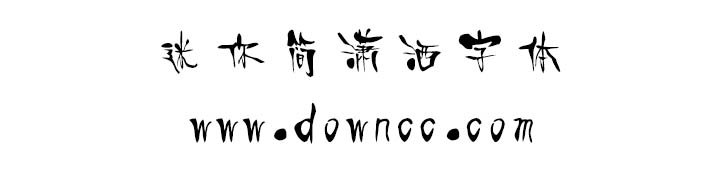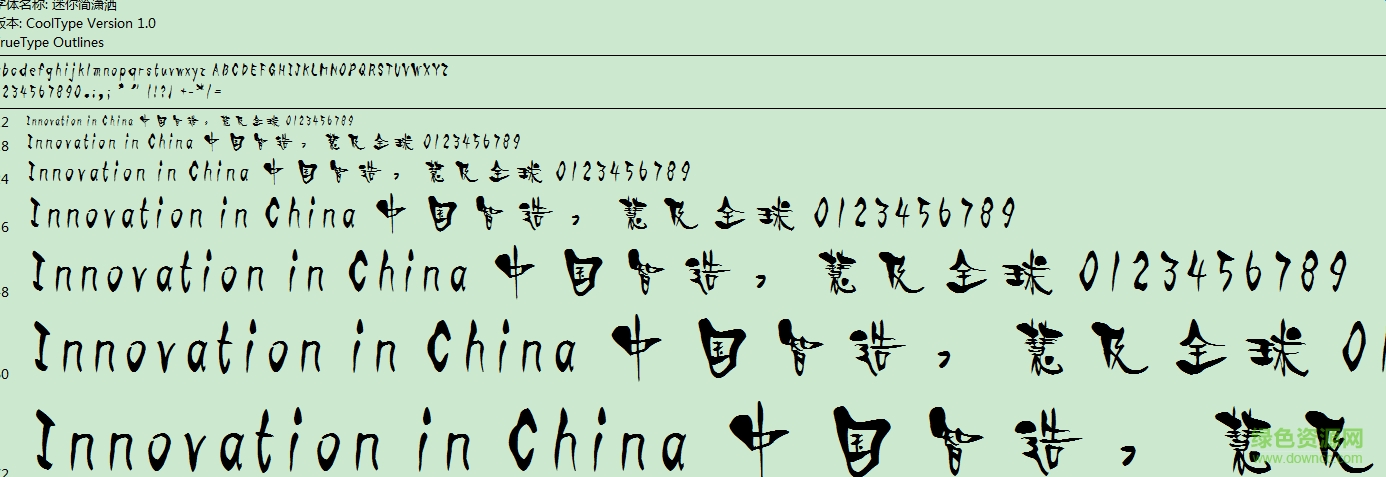
迷你簡瀟灑字體是一款非常寫意的字體表現(xiàn)手法,是一款非常有趣的藝術(shù)字體,有需要的朋友可以來綠色資源網(wǎng)免費(fèi)下載哦!這里還有更多有趣的字體等你到綠色資源網(wǎng)來體驗(yàn)!
迷你簡瀟灑字體一款非常獨(dú)特的迷你藝術(shù)字體,它不僅造型奇特,字體線條粗細(xì)不一,而且這款字體的筆畫鋒利,大氣,字體結(jié)構(gòu)引人注目,整體效果顯得特別出色